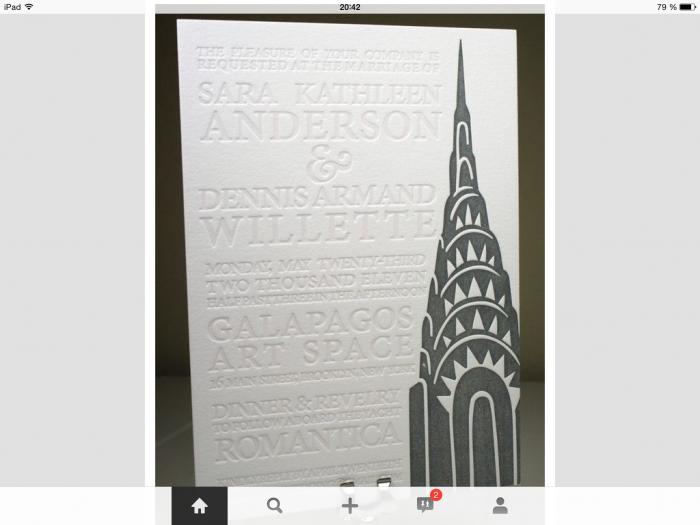
Schrift ähnlich der Garamond(?)
Ach was!
Die Minion kenn ich natürlich. So edel hätte ich der Minion gar nicht zugetraut
Um das & ging es mir aber auch primär :-/ ne Idee dazu?
könnte das hier sein:
https://www.myfonts.com/fonts/p22/parrish-roman/roman/?meta=/31383/%26/P22+Parrish+Roman